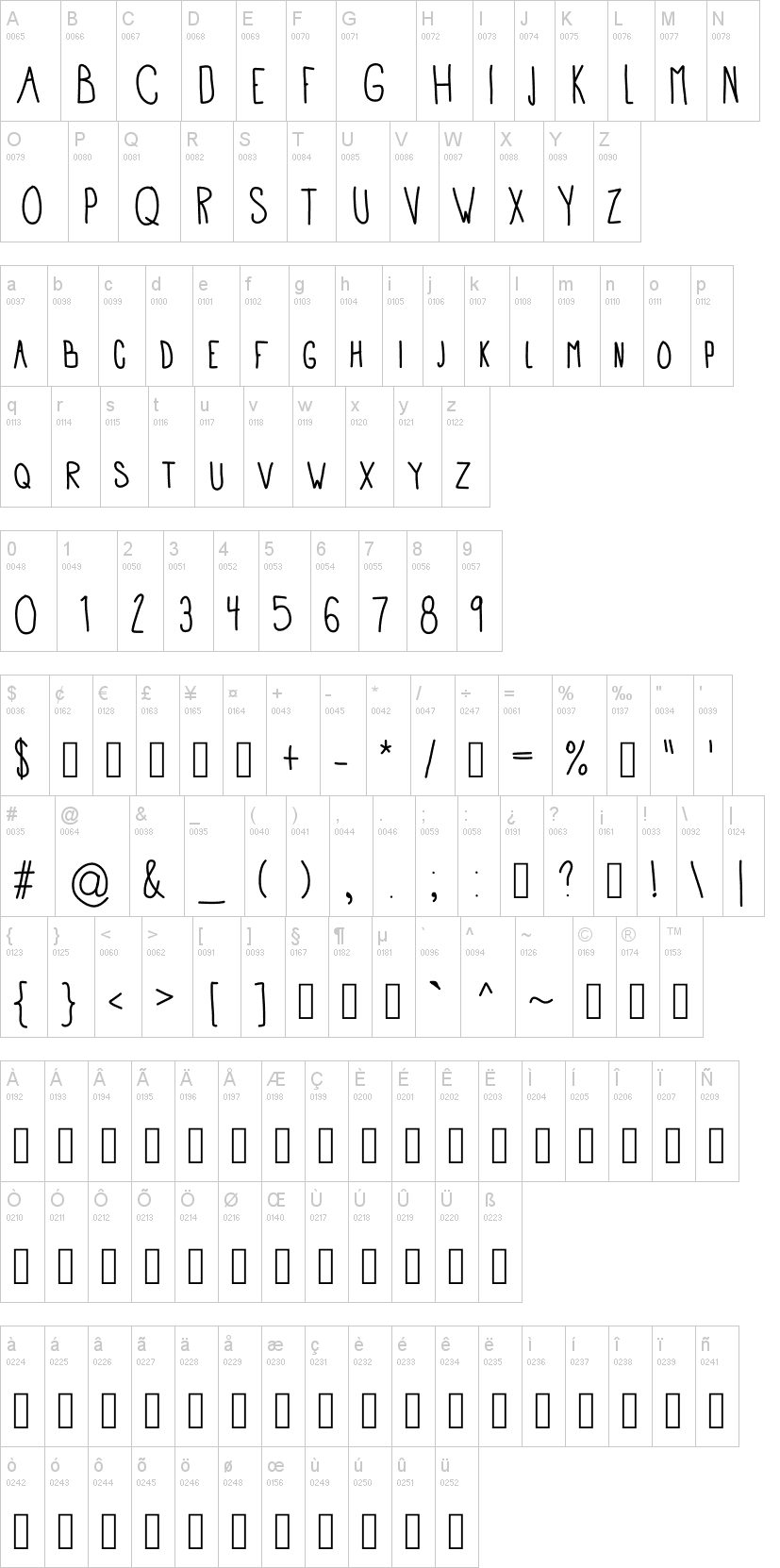
APD字体是一种字体家族,由设计师Alf Becker在20世纪20年代和30年代创建。这个字体家族被称为"Alphabet and Lettering",它是一种装饰性的手写字体,常用于海报、书籍封面、广告等方面。APD字体的特点是笔画线条流畅,可读性好,而且具有很强的艺术感和个性化。因此在设计、平面广告和艺术等方面得到广泛应用。内容介绍
APD是一款非常不错的手写艺术字体,具有很好的视觉感,适合于文化类的宣传设计、商业类品牌的广告和产品包装设计以及个性化文字排版等较多场景。